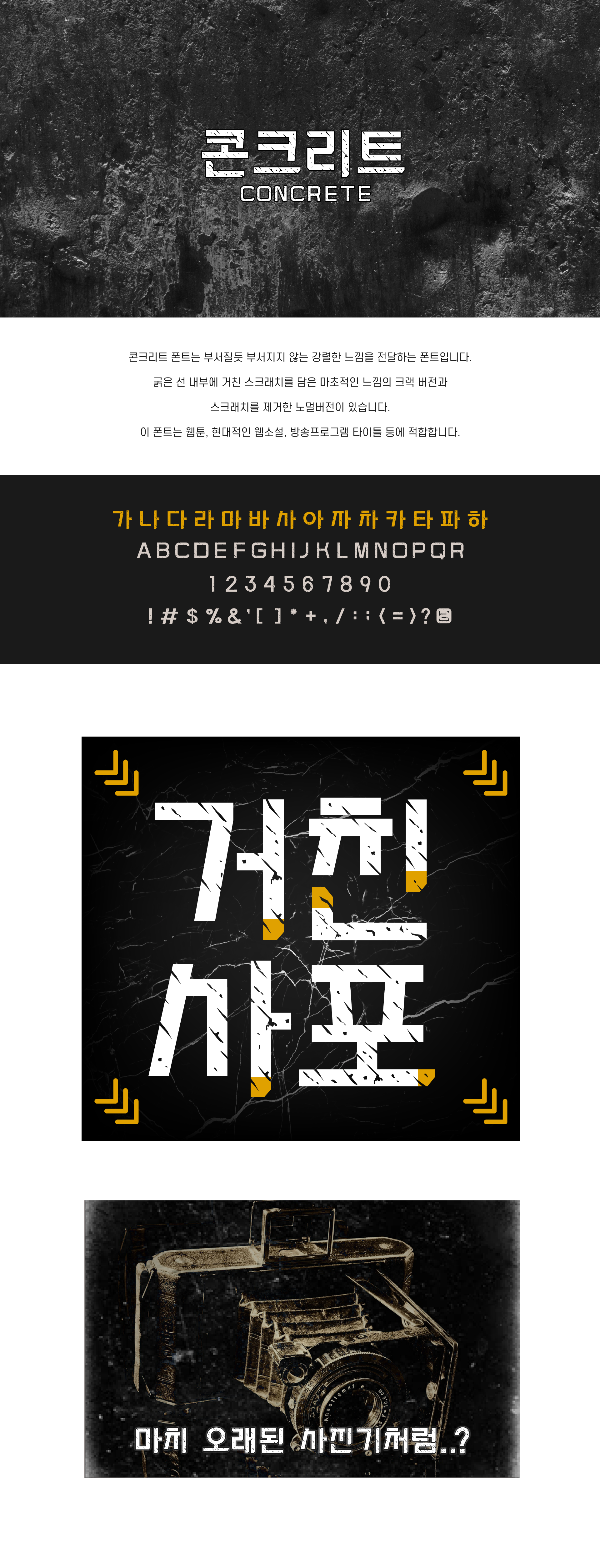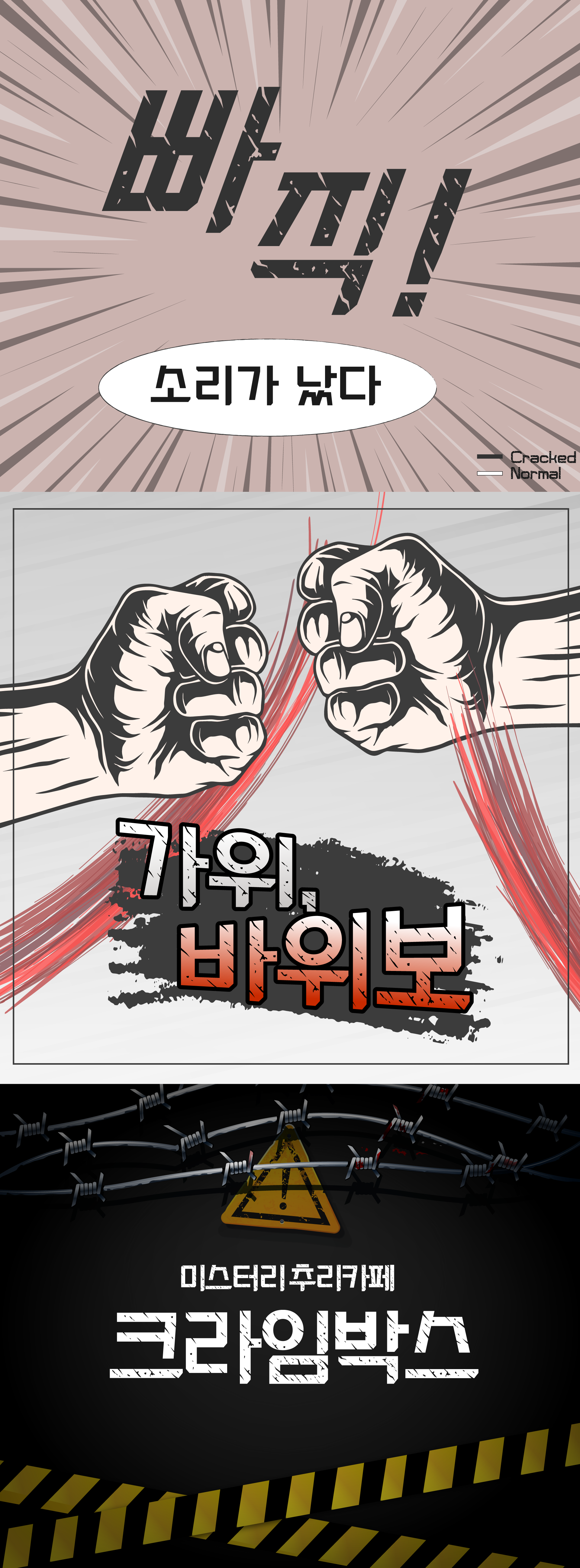
콘크리트 폰트는 부서질듯 부서지지 않는 강렬한 느낌을 전달하는 폰트입니다. 굵은 선 내부에 거친 스크래치를 담은 마초적인 느낌의 크랙 버전과 스크래치를 제거한 노멀버전이 있습니다. 이 폰트는 웹툰, 현대적인 웹소설, 방송프로그램 타이틀 등에 적합하며, 콘크리트 느낌의 폰트(Cracked)와 속이 채워진 노멀 폰트(Normal)로 제공됩니다.